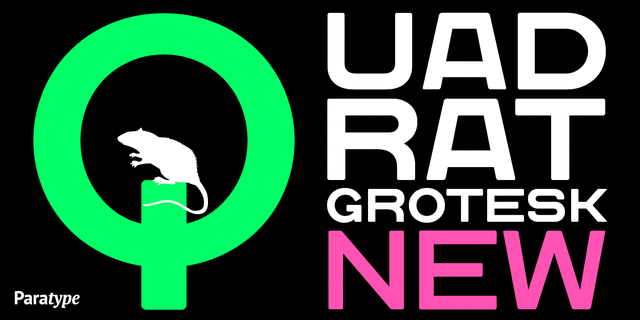
ПТ Квадрат Гротеск™ Шрифт разработан для фирмы ParaType в 2001 году Владимиром Павликовым. Имеет широкие квадратные знаки, за что и получил свое название. Прототипом послужил один из старых русских деревянных шрифтов. Это шрифты крупных кеглей для набора афиш, изготовлявшиеся из дерева. В их оттисках сохранялась текстура дерева и следы эксплуатации, что отражено в формах знаков шрифта Квадрат Гротеск. Предназначен для акцидентного набора.